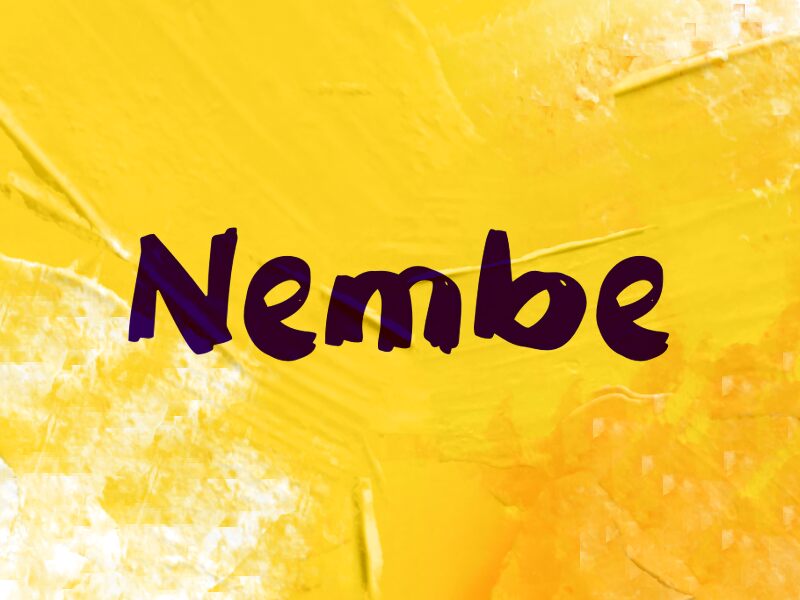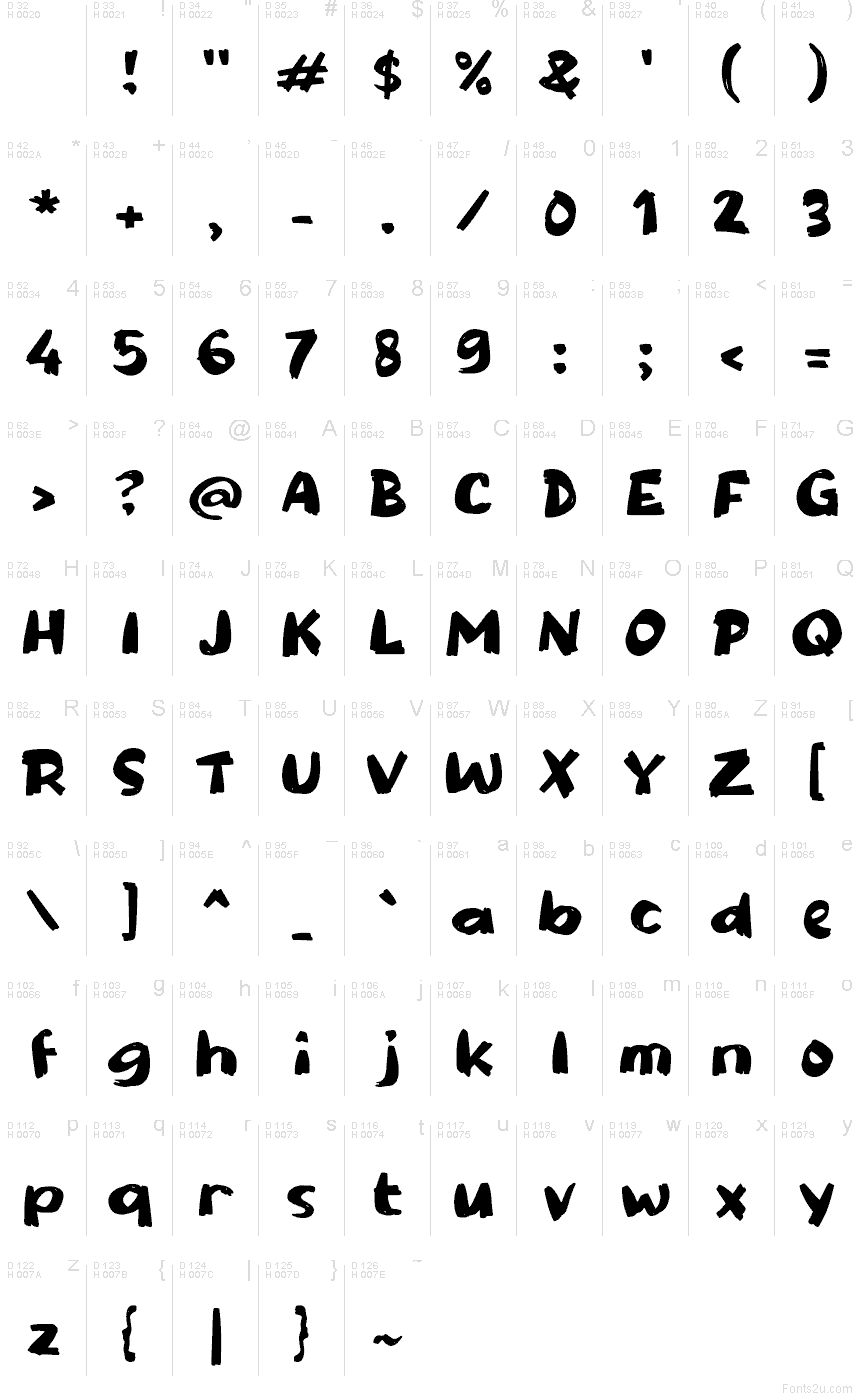
Nembe
Nembe di Wep è un font brush gratuito con un carattere ruvido, dipinto a mano e una presenza corposa, ricca di inchiostro. Le lettere appaiono larghe e urgenti, con bordi irregolari, curve piene e un ritmo informale che mantiene il font vivace anziché rifinito.
È perfetto per poster, grafiche musicali, streetwear, copertine di fanzine, branding di caffetterie e brevi titoli sui social, dove quel dinamismo pittorico riesce a trasmettere il messaggio con forza.
Essendo un font gratuito, Nembe dà il meglio di sé in contesti brevi come titoli, copertine e grandi citazioni, perché i tratti spessi e la texture a pennello libera donano anche alle parole più semplici una voce diretta e artigianale.